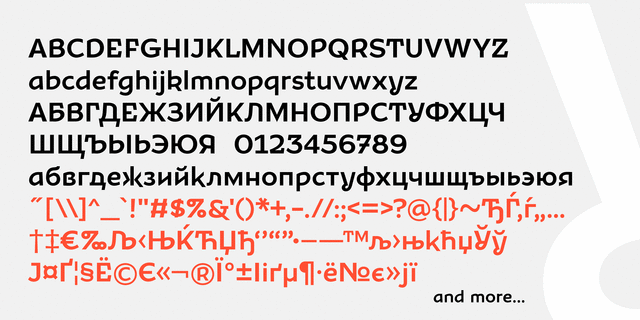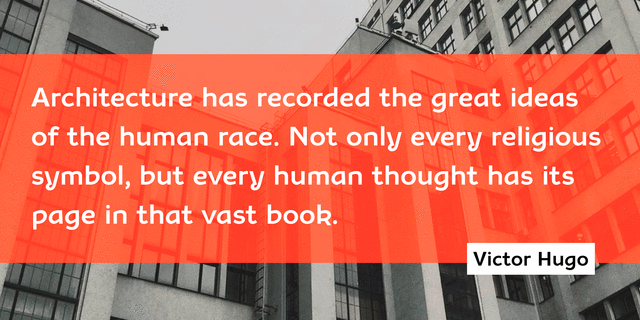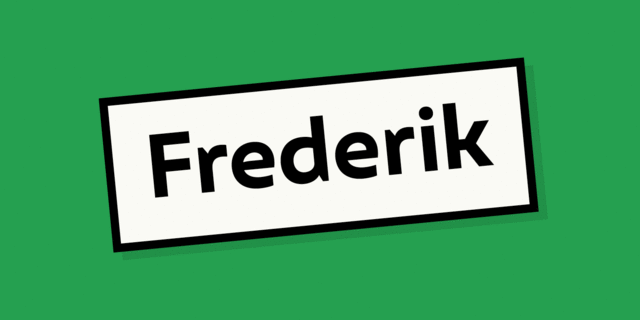
Aleksa – шрифтовое семейство, сочетает в себе сдержанность гуманистического гротеска и игривость традиционных украинских форм начала 20 века. Такой контраст делает шрифт необычным, динамичным и приятным на вид. Гарнитура состоит из 9 насыщенностей (от супертонкой до ультражирной), а также курсивы. Это универсальный гротеск, прекрасно работает во многих видах дизайна, от логотипов до наборных текстов. Семейство разработали Кирилл Ткачев и Марчела Можина в 2020 году.